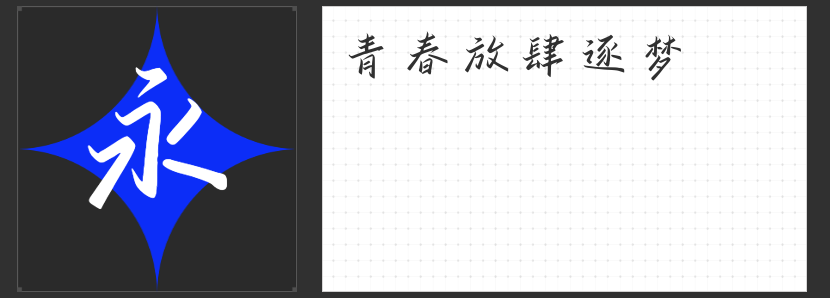
字体的力量:打造独特品牌标识的四款精选字体
在品牌建设的过程中,Logo设计是至关重要的一步。它不仅是品牌的视觉代表,更是品牌形象和价值传递的重要媒介。而Logo中的文字部分,其字体选择更是直接影响着品牌的个性表达。今天,就让我们一起来探索四款极具特色且适合Logo设计的字体,看看它们如何能够帮助你的品牌故事更加生动有趣。
1. 造字侠热辣隶简
这款字体以其独特的隶书风格,结合了现代设计的简洁与传统书法的艺术感,展现出一种既有历史厚重感又不失时尚气息的独特魅力。它的笔画流畅自然,结构紧凑而不失灵动,非常适合那些希望在经典与现代之间找到平衡点的品牌。无论是餐饮业还是文化行业,使用“造字侠热辣隶简”作为Logo设计的字体,都能够让人眼前一亮,感受到品牌的热情与活力。
2. 造字侠朝凤宋简
“造字侠朝凤宋简”则是一款更偏向于传统审美的字体,它继承了宋代刻本的优雅与精致,同时又通过简化处理,使得字体更加清晰易读。这款字体适用于那些追求高端、典雅形象的品牌,如珠宝、奢侈品、高端酒店等。它能够赋予品牌一种古典与现代交融的独特气质,让Logo在众多设计中脱颖而出,成为品牌识别度极高的标志。
3. 字青春逐梦简 准粗
如果你的品牌面向年轻市场,那么“字青春逐梦简 准粗”绝对是一个不错的选择。这款字体采用较为粗犷的笔触,给人以力量感与冲击力,同时也透露出一种积极向上的态度。它非常适合运动品牌、潮流服饰或是科技公司等,能够很好地传达出品牌的活力与创新精神,激发目标客户的共鸣。
4. 造字侠醉春风简繁 苍劲
最后介绍的是“造字侠醉春风简繁 苍劲”,这是一款充满艺术感的手写体,笔画粗细变化丰富,整体呈现出一种随性洒脱的风格。对于那些注重个性表达、追求独特艺术氛围的品牌来说,这款字体无疑是最佳之选。它可以广泛应用于艺术工作室、独立设计师、文化创意产品等领域,不仅能够提升品牌的艺术格调,还能加深消费者对品牌的印象。
综上所述,不同的字体选择能够为品牌带来截然不同的视觉效果与情感体验。因此,在进行Logo设计时,根据品牌定位及目标受众的特点精心挑选合适的字体,将有助于塑造更加鲜明、更具吸引力的品牌形象。希望上述推荐能为您的品牌建设之路提供一些灵感与帮助。